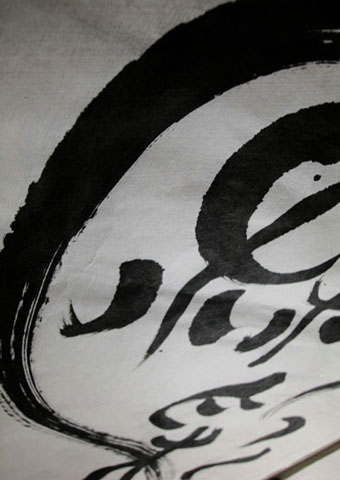
| 贈り物としてご依頼頂いた作品です。「麻」はお母さんの、「彩」は娘さんのお名前の頭文字。母の深い愛で娘が守られているような優しいイメージでということでしたので、それにお互いが心の支えになっているというイメージをプラスして書きました。象形文字に近い篆書(てんしょ)体をベースに創作、ハートっぽく見えるのがポイント! 今回は、贈り主の岩崎さまと、実際に書を手にされた「麻」さまからも写真つきのお礼のメールを頂き、心があったかくなったオカモトでした〜。 | |